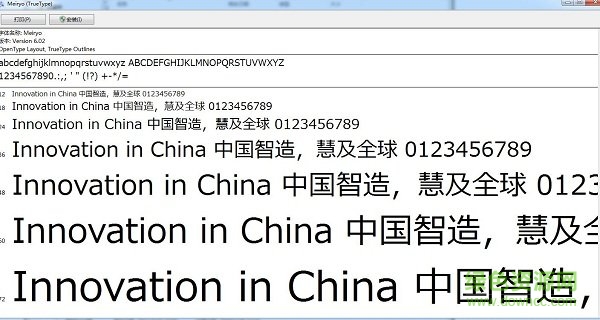
メイリオ字體又叫明瞭體,是一款好用的日本電腦系統(tǒng)字體,和中文黑體字體很像,最大的特點(diǎn)是清晰度高,字體邊緣調(diào)整后也不會(huì)模糊,常常用于屏幕顯示,歡迎大家免費(fèi)下載!
メイリオ是一種附設(shè)在 微軟 Windows Vista的 OpenType 日語字體,原檔案名稱為 meiryo.ttc,屬于無襯線字體和黑體(ゴシック體)的一類。它的設(shè)計(jì)配合了 Windows Vista 的 ClearType 晶瑩畫面,并包含了 JIS X 0213:2004 字集的漢字。
原來的MSゴシック等字體,在大約9pt的大小就使用點(diǎn)陣字體顯示,這也是為了保證可讀習(xí)慣的一種嘗試。但是,由于沒有抗鋸齒、間距調(diào)整、平滑調(diào)整等效果使得字體美觀受到影響,而且制作字體的成本、文件容量的增大也是一大問題。原操作系統(tǒng)中對于沒有準(zhǔn)備點(diǎn)陣的字體實(shí)施抗鋸齒等調(diào)整后反而會(huì)使小字號的字體邊緣崩潰,看不清楚。